如果你的操作系统是Windows XP,那么你可以调节系统字体显示的清晰度(ClearType),使之适合你的显示器,达到最佳的显示效果。这只需要几个简单步骤
可以选择使用中文版Vista新设微软雅黑字体 单价百美元1字 这篇文章中的方法开启ClearType功能,也可以使用以下方法。
一、调节系统字体的显示清晰度
调节方法很简单,在微软公司的网页上调节ClearType字体即可,下面会一步步介绍如何调节。
页面显示调节的第一步 Step 1: Turn on Windows XP ClearType (开启Windows XP的ClearType功能)复选页面底部的Turn on ClearType(开启ClearType),然后点击Next按钮
2) 进入Step 2: Select ClearType configuration(选择ClearType配置类型)后,有两幅图显示不同方案下的显示效果
左边为使用RGB的ClearType方案,右边为BGR
哪副图看起来清楚,没有重影,就点击选择哪边
推荐选择左边的RGB
然后点击Next按钮进入下一步
3) 进入Step 3: Tune ClearType settings (调节ClearType设置)
一共有6幅图,显示不同的ClearType重量等级情况下的文字显示情况,字如在你觉得显示效果最佳的文字显示图上点击,选中此种方案,选中后图片周围的边框会加粗
然后选择Finish即可
此时ClearType字体调节完成,你可以马上从浏览器界面上的文字变化看出来效果,如果不满意,可以后退到Step3重新选择别的图
三、ClearType原理几句话简介
关于ClearType的介绍充满了神话和传说,其实这东西简单的很,就是为文字轮廓加入一些补偿像素,使文字看起来平滑圆润。
下面这张图可以看到文字开启和关闭ClearType处理时候显示的效果,开启后文字变得圆滑起来
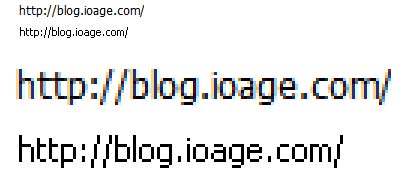
另外:有些介绍中说的ClearType技术只对液晶显示屏才有效,对传统CRT反而使文字变得不清楚 - 这是错误的理解。其实它对哪种显示屏起的作用都一样,如果你喜欢它,那么CRT显示屏同样可以开启。只不过对于液晶显示屏,由于像素都是方形,所以开启后效果更好一些,而由于有的CRT显示屏由于聚焦本身就不清晰,所以才会让人觉得反而开启后失真。